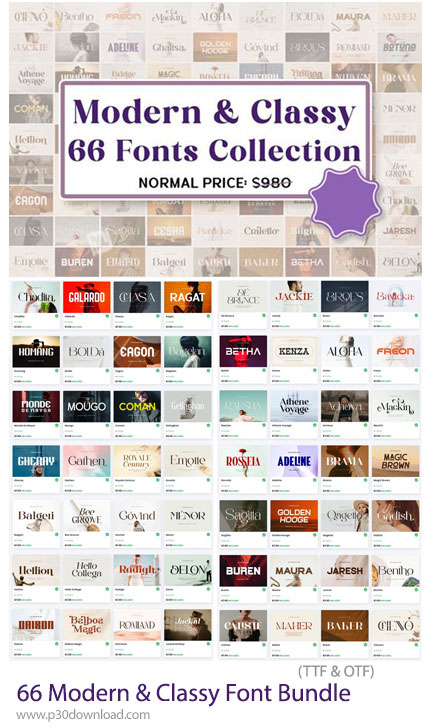
این مجموعه شامل 66 فونت حرفهای و ممتاز است که با دقت برای طراحان گرافیک، برندها، و تولیدکنندگان محتوای لوکس طراحی شدهاند و با فرمت های OTF و TTF بر روی سایت برای دانلود قرار گرفته است. این بسته، ترکیبی از فونتهای مدرن، مینیمال، ظریف و کلاسیک را ارائه میدهد که برای ایجاد هویت بصری خاص و حرفهای در هر پروژهای فوقالعاده هستند. با استفاده از این پک میتوانید به راحتی طراحیهایی انجام دهید که حس شیک بودن، اعتماد، ظرافت و مدرن بودن را القا کند. این مجموعه یکی از بهترین انتخابها برای برندهای فشن، آرایشی، هنری، طراحی داخلی، جواهرات، و محصولات لوکس است.